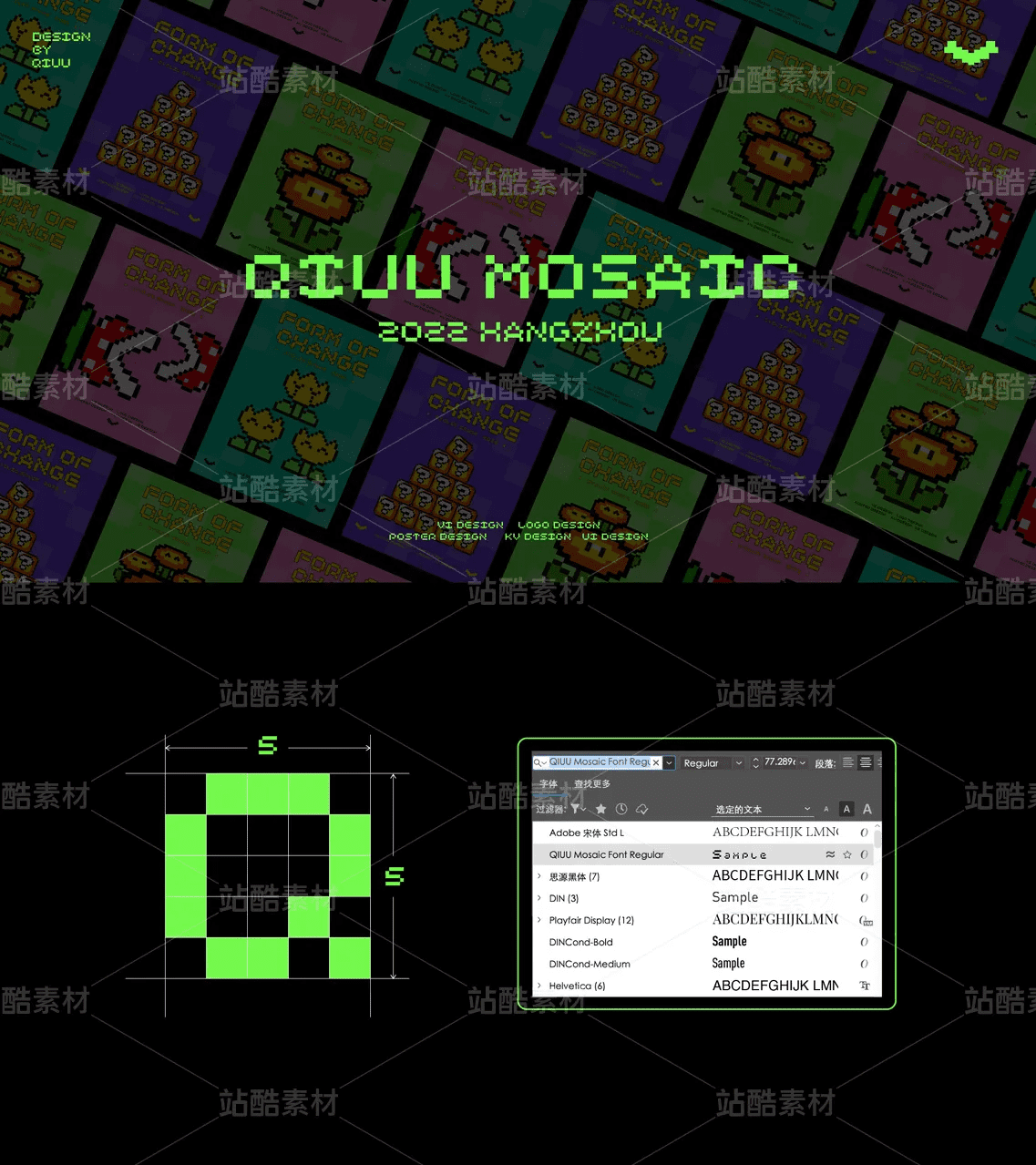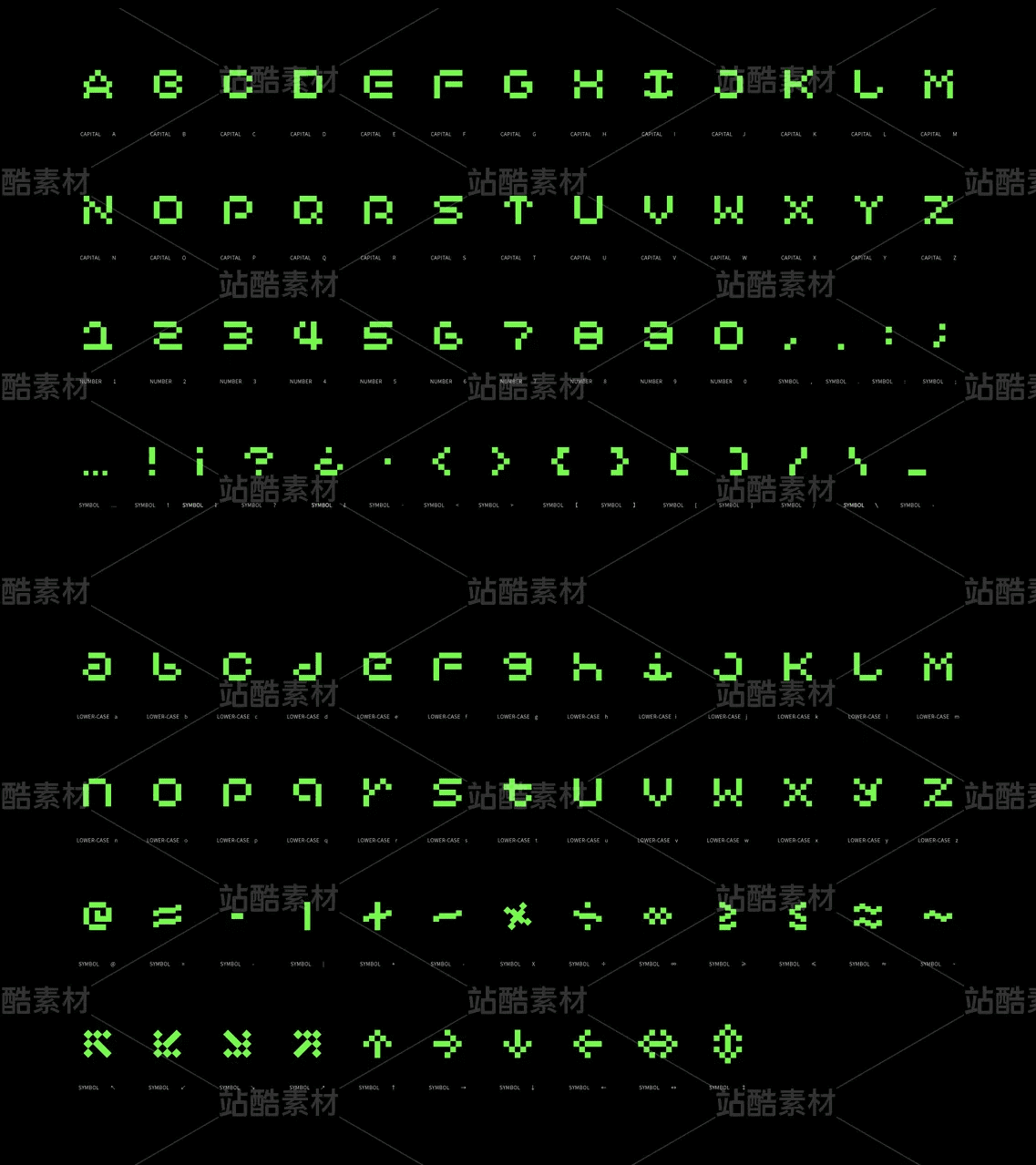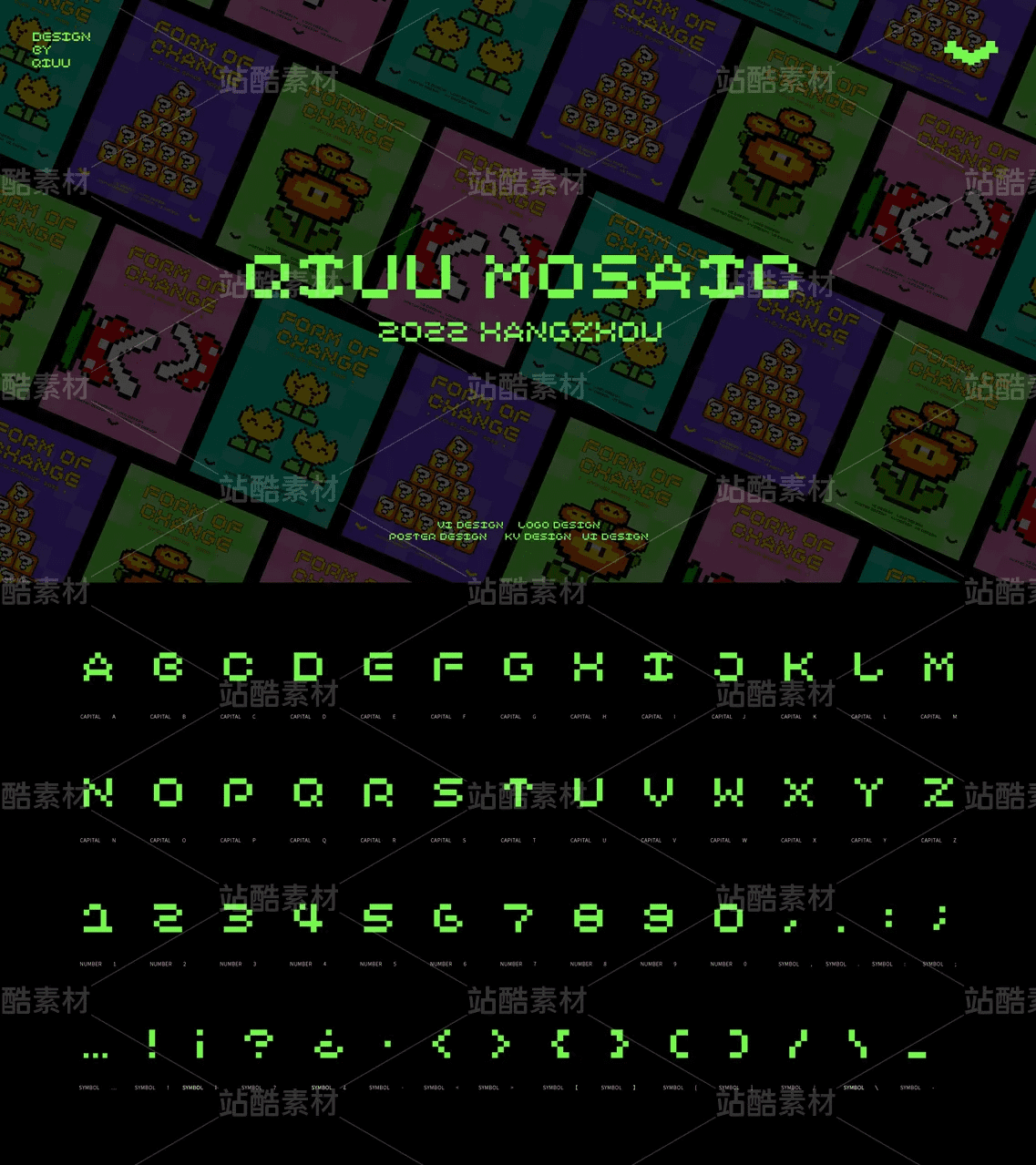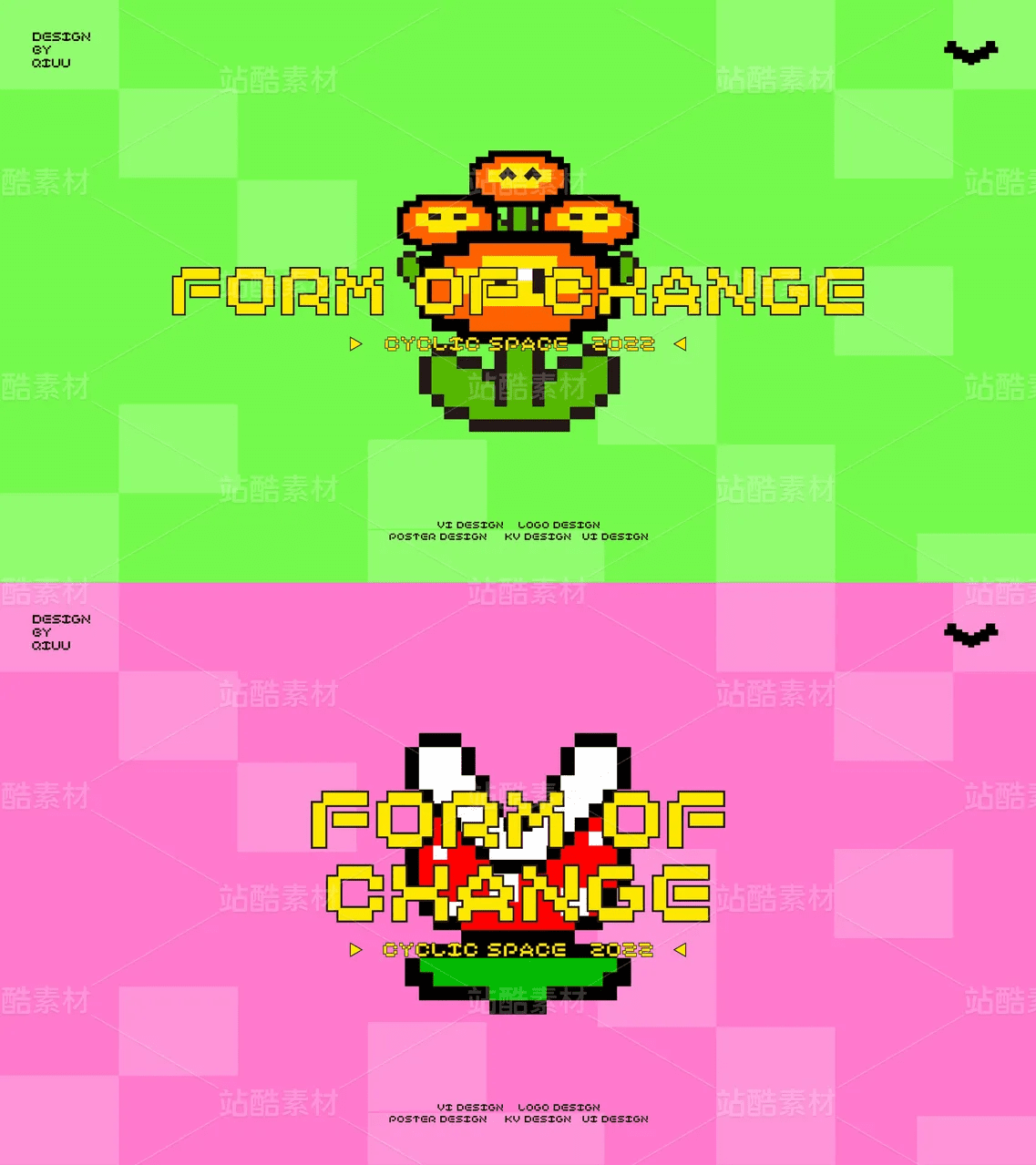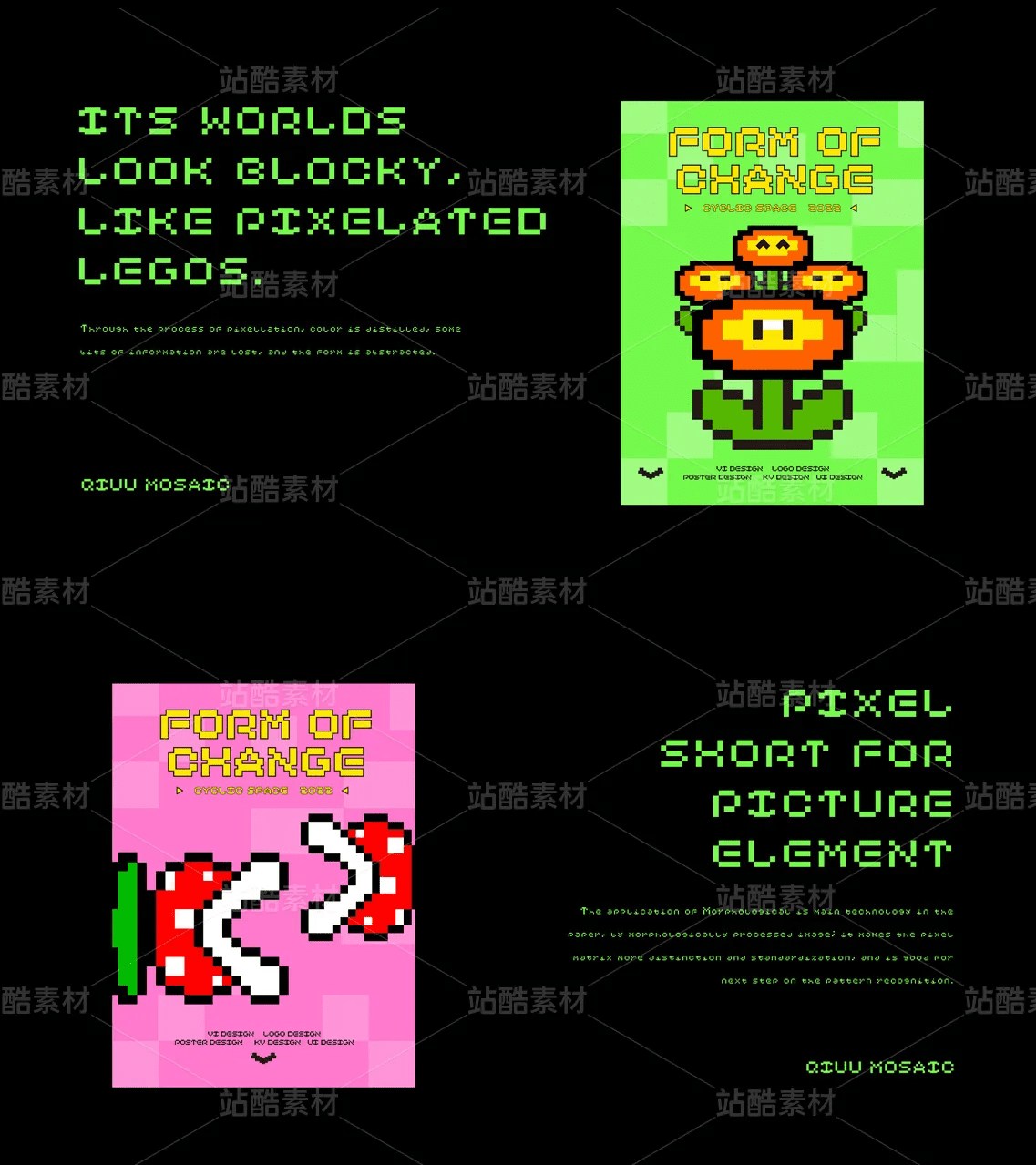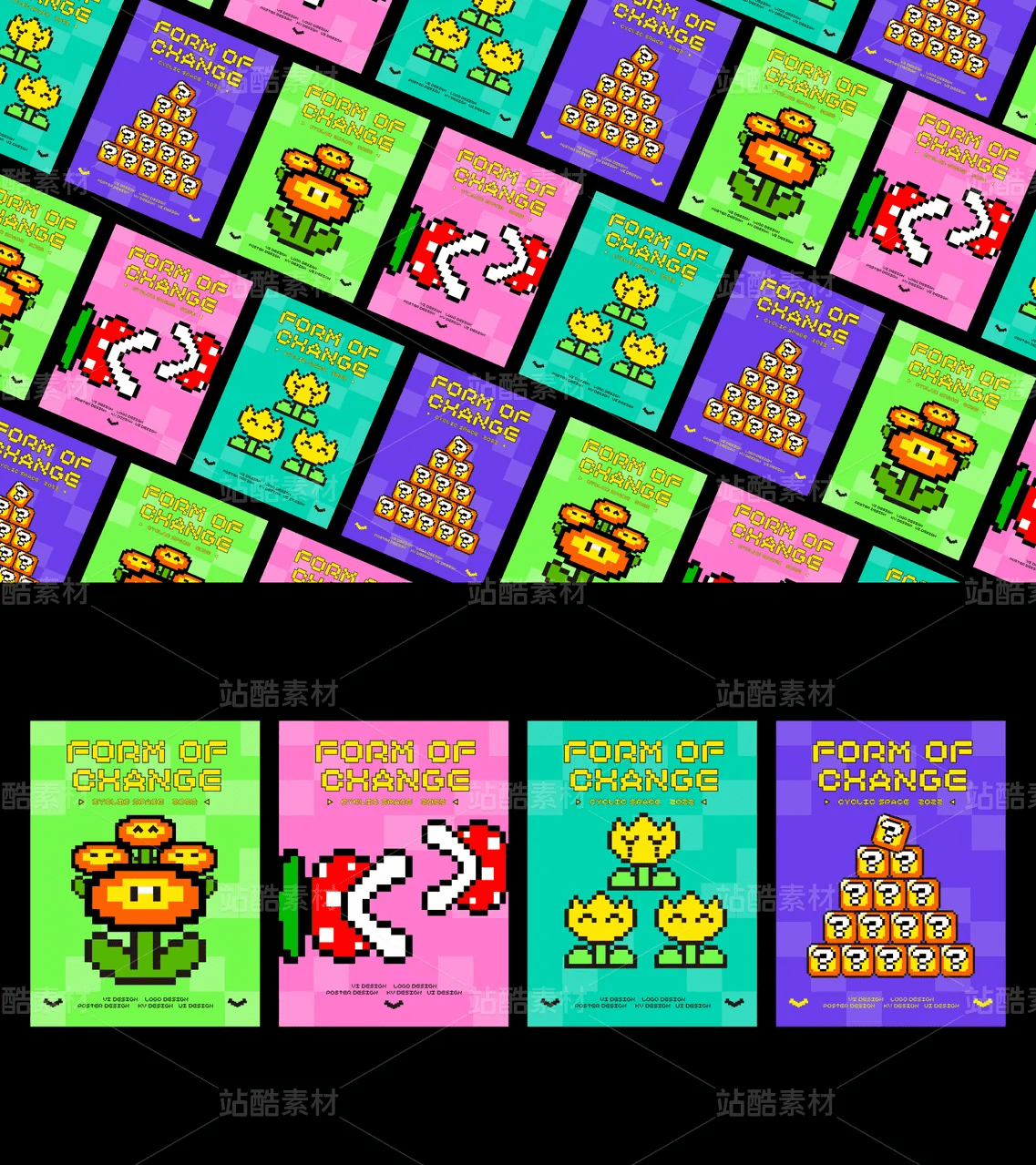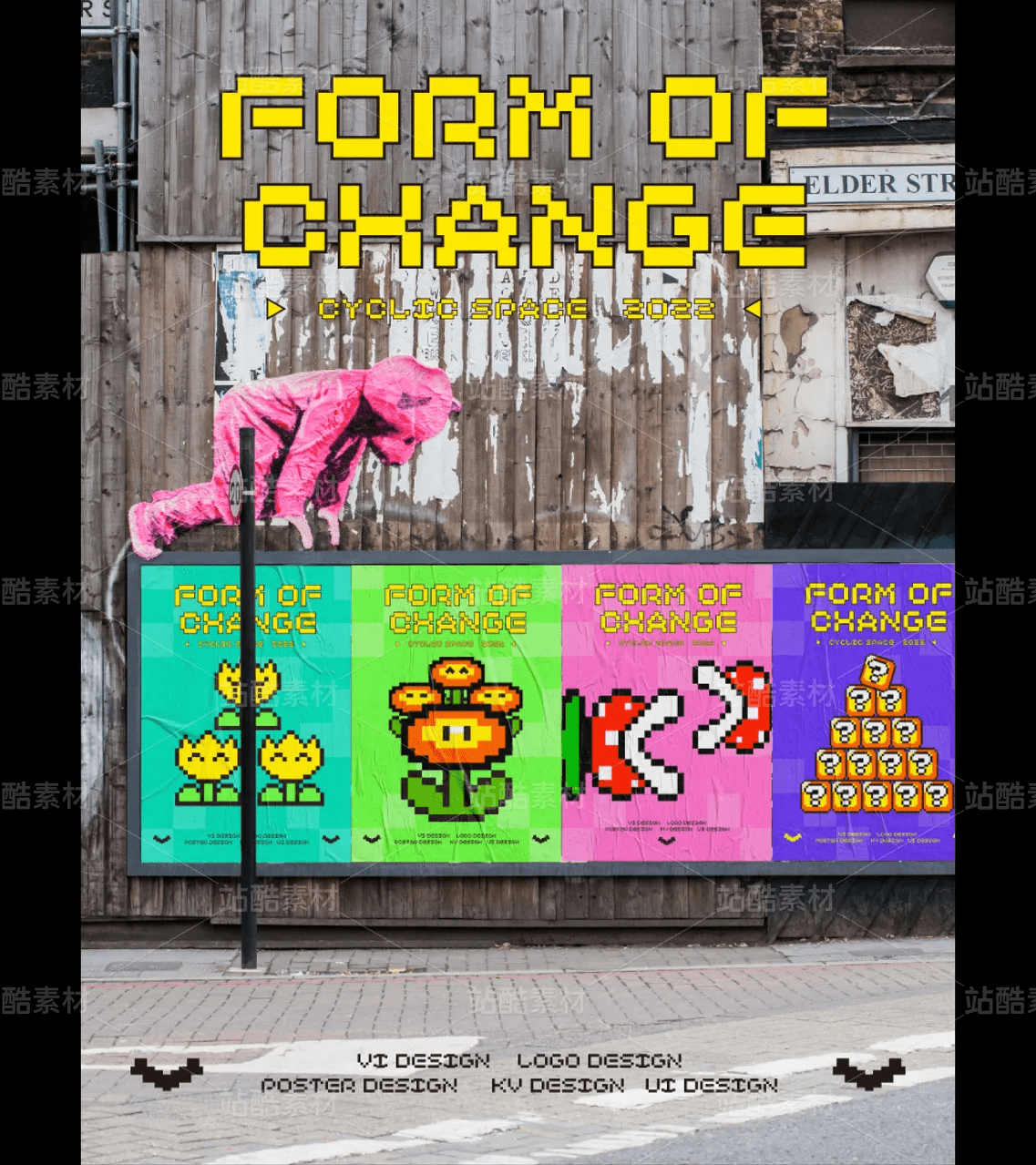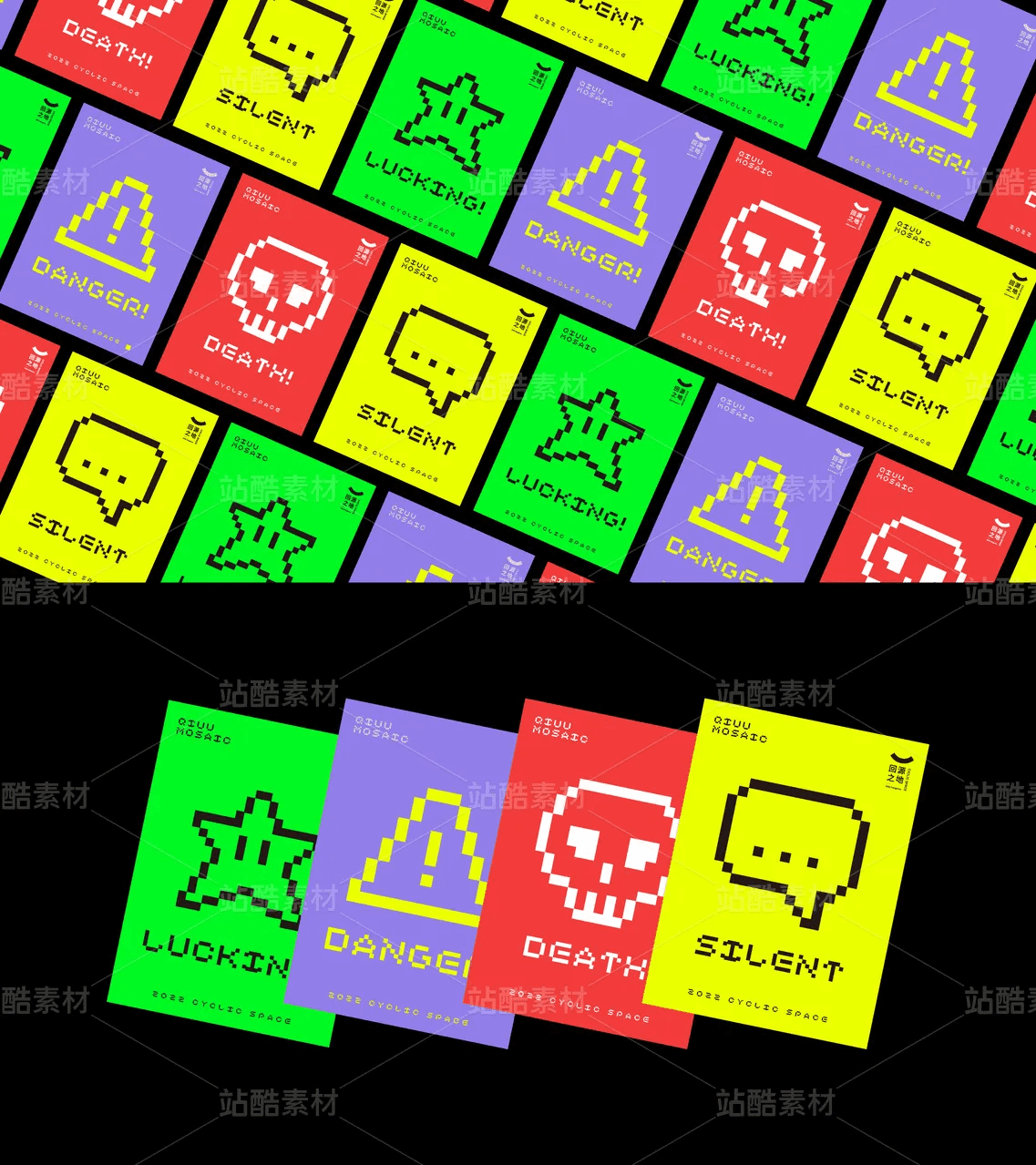
Font Pixel QIUU 5×5 – Font chữ mosaic chất lượng cao với tỷ lệ chuẩn 5×5 pixel, được cấp phép sử dụng hoàn toàn miễn phí cho mọi dự án cá nhân và thương mại. Lý tưởng cho thiết kế game, logo, banner quảng cáo và các dự án sáng tạo yêu cầu phong cách pixel art độc đáo.
Tính năng nổi bật:
- ✓ Tỷ lệ chuẩn 5×5 cho mọi ký tự
- ✓ 125 ký tự đầy đủ (chữ hoa, chữ thường, số, ký hiệu)
- ✓ Thiết kế nhất quán giữa các ký tự